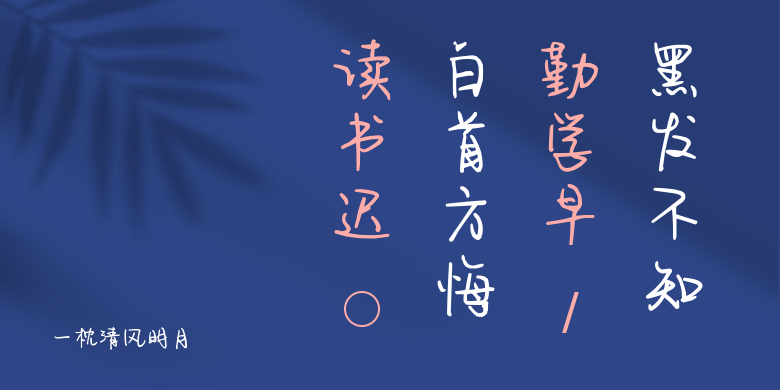
一枕清风明月
一枕清风明月,这款字体结构工整、笔画清晰,兼顾美观与易读性,适用于标题、正文、海报、包装、LOGO 等多种场景。字形优雅稳定,风格百搭耐看,适配日常排版与创意设计,让文字呈现更舒适、更具质感。一枕清风明月一笔一画,皆是细节,以均衡的比例、流畅的线条打造舒适视觉体验,字形端正大气,风格简约现代。无论是商业设计、品牌宣传还是日常排版,都能轻松驾驭,让文字更有格调与力量。一枕清风明月字体下载。